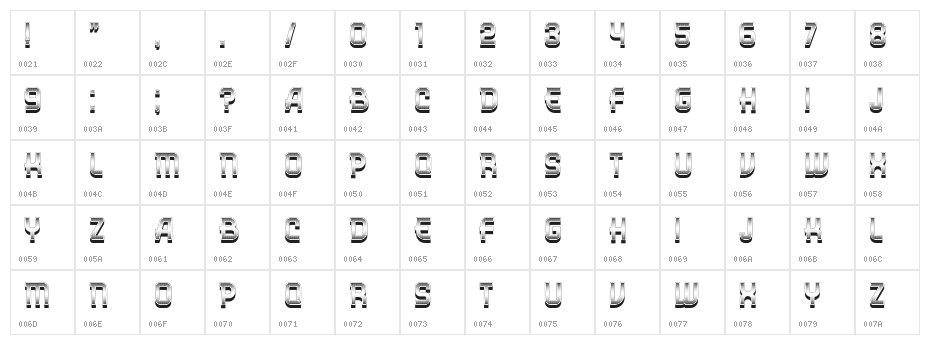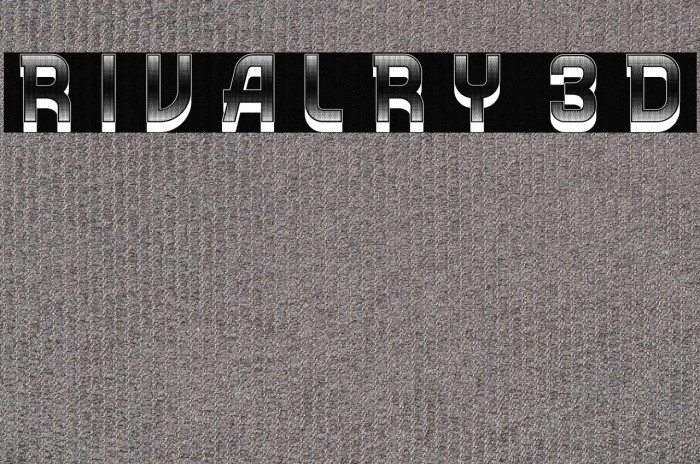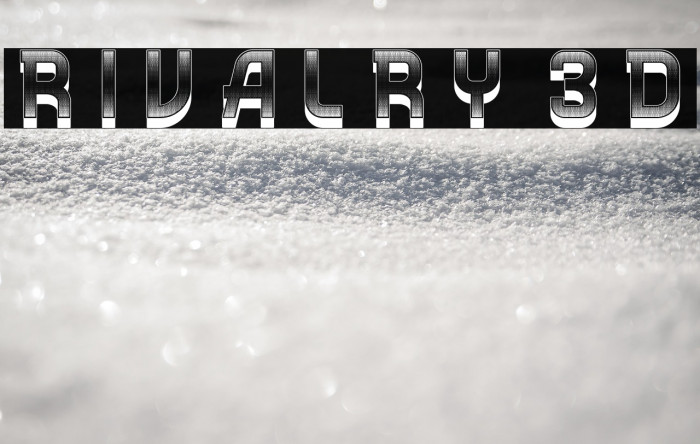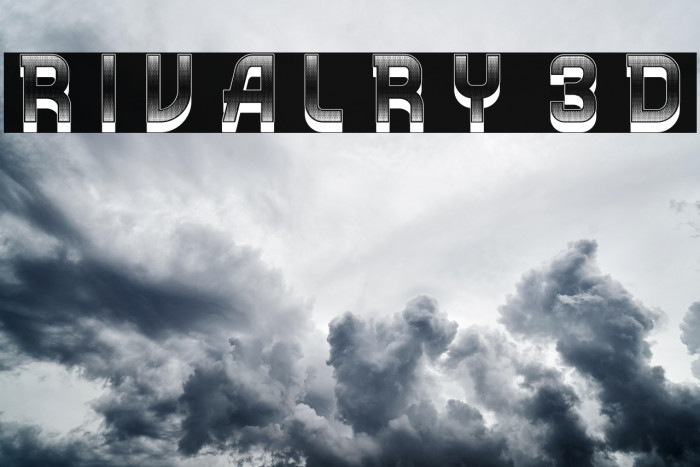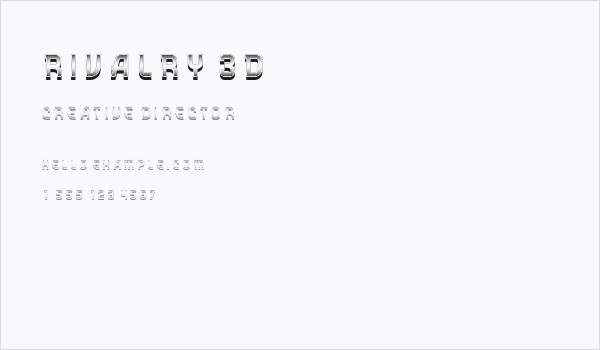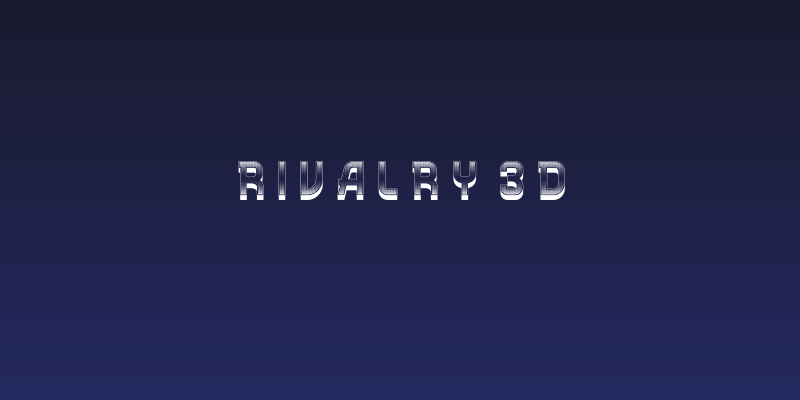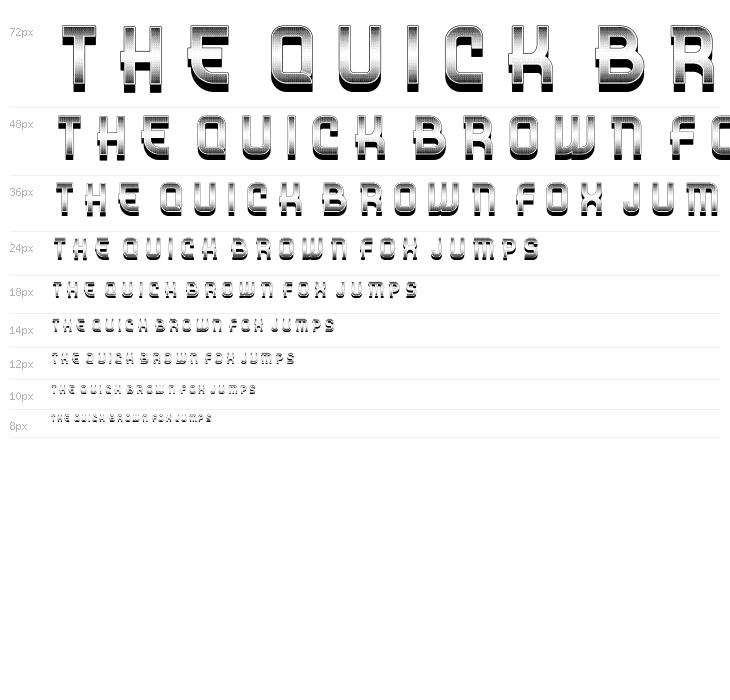
Rivalry 3D Font
| Stil general | Futuristic, Industrial |
| Proiecte propuse | Ideal for video game titles, movie posters, technology branding, and any project needing a strong, futuristic aesthetic. |